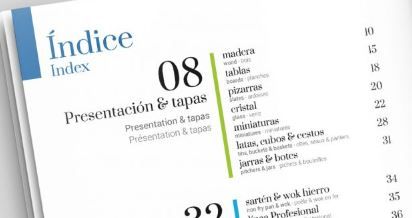
Sí es Bodoni. Puede ser que se trate de una variación de la Bodoni identificable en algún aspecto (tal vez sea más estrecha, o ese et sea más florido de lo común) porque hay diversas Bodoni de distintas fundiciones (Boboni Book, Libre Bodoni, Boboni Std, Bauer Bodoni, etc.), pero tiene todos los elementos que identifican a una Bodoni o , como mínimo, a una didona.
Suranna
Sí es Bodoni. Puede ser que se trate de una variación de la Bodoni identificable en algún aspecto (tal vez sea más estrecha, o ese et sea más florido de lo común) porque hay diversas Bodoni de distintas fundiciones (Boboni Book, Libre Bodoni, Boboni Std, Bauer Bodoni, etc.), pero tiene todos los elementos que identifican a una Bodoni o , como mínimo, a una didona.
No es Bodoni
Bodoni.